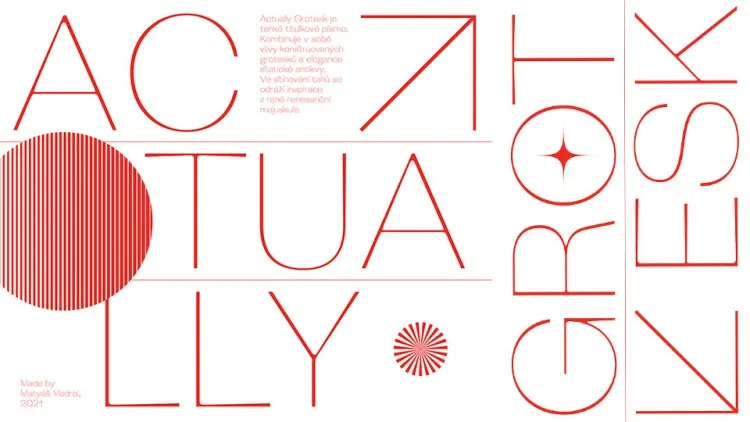
Esta fonte ‘Actually Grotesk Font’ é uma tipografia sans serif moderna. É clara, delicada e clássica, projetada pelo Matyáš Vedral e compartilhada pela 99designs. Ela oferece um contrastes entre os tipos de serif sem-serif, inspirada em grotesques modernos suíços e fontes serifadas clássicas. A fonte vem na versão ‘Thin’, ideal para uso em tamanhos maiores. Seja você designer de sites ou impressões digitais, esta fonte será uma escolha inteligente. Ela é perfeita para textos de destaque ou se tornar o tom fundamental de seu design digital.